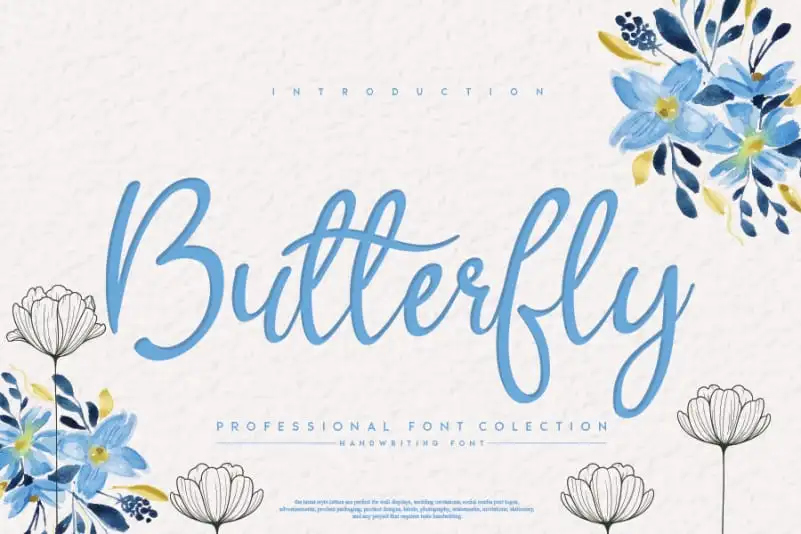
Butterfly Script Font – Download Grátis
A Butterfly Script Font é uma elegante escolha para quem procura afeição imediata. Ela transmite claramente sua influência na calligrafia enquanto mantém um toque atual e fresco, tornando-a uma opção indispensável para projetos de escrita à mão livre. Esta fonte, cuidadosamente criada pelo designer Andikastudio, é perfeita para quem busca dar um toque especial em seus trabalhos. Enganche-se nessa fonte e traga suas criações ao topo!